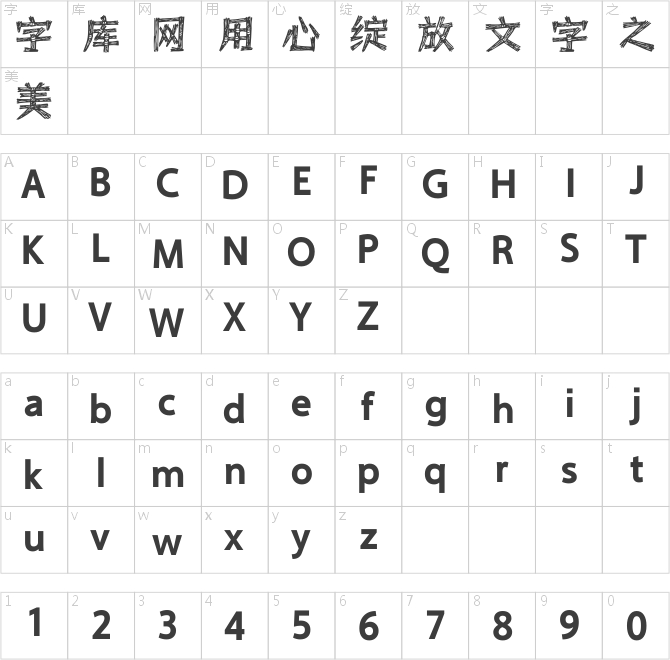
“孤舟蓑笠翁,獨(dú)釣寒江雪”。本款字體用粗獷、原生態(tài)的筆畫(huà)線條,去模擬垂釣老翁身披蓑衣之狀。每個(gè)字都具有擬人化的效果,而且字體的結(jié)構(gòu)吸納了POP字體的一些特點(diǎn),在字形上顯得不呆板,生動(dòng)有趣、靈動(dòng)活潑,具有“象形”意味。字中有畫(huà),字畫(huà)結(jié)合,特別適合用于創(chuàng)意類(lèi)以及兒童相關(guān)的廣告設(shè)計(jì)、產(chǎn)品包裝等。
作者張惟梓,擅長(zhǎng)繪畫(huà)、攝影及美術(shù)字設(shè)計(jì)等,長(zhǎng)期從事企業(yè)文化、宣傳及產(chǎn)品設(shè)計(jì)開(kāi)發(fā)工作,攝影及美術(shù)作品曾多次參加省市級(jí)展覽。